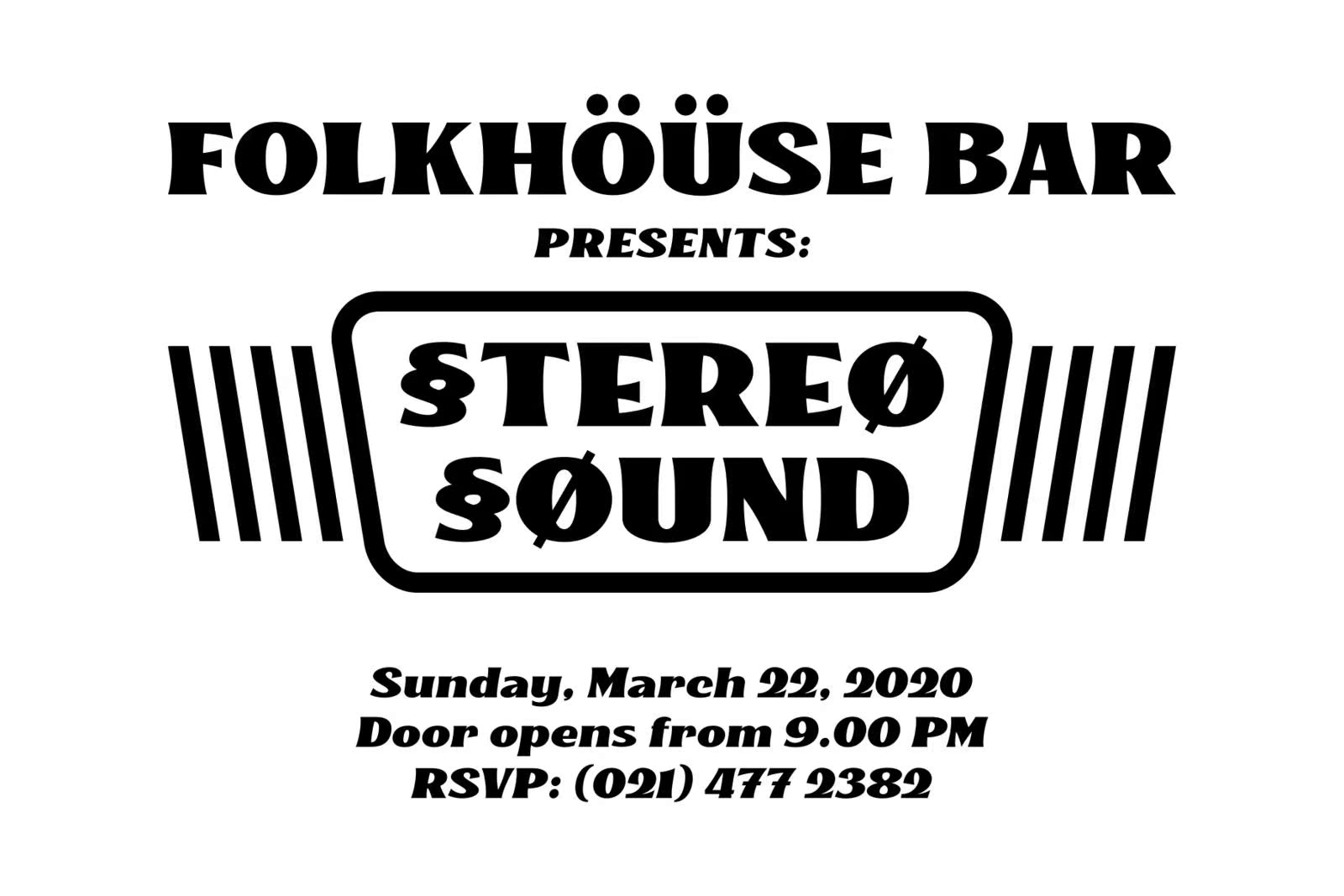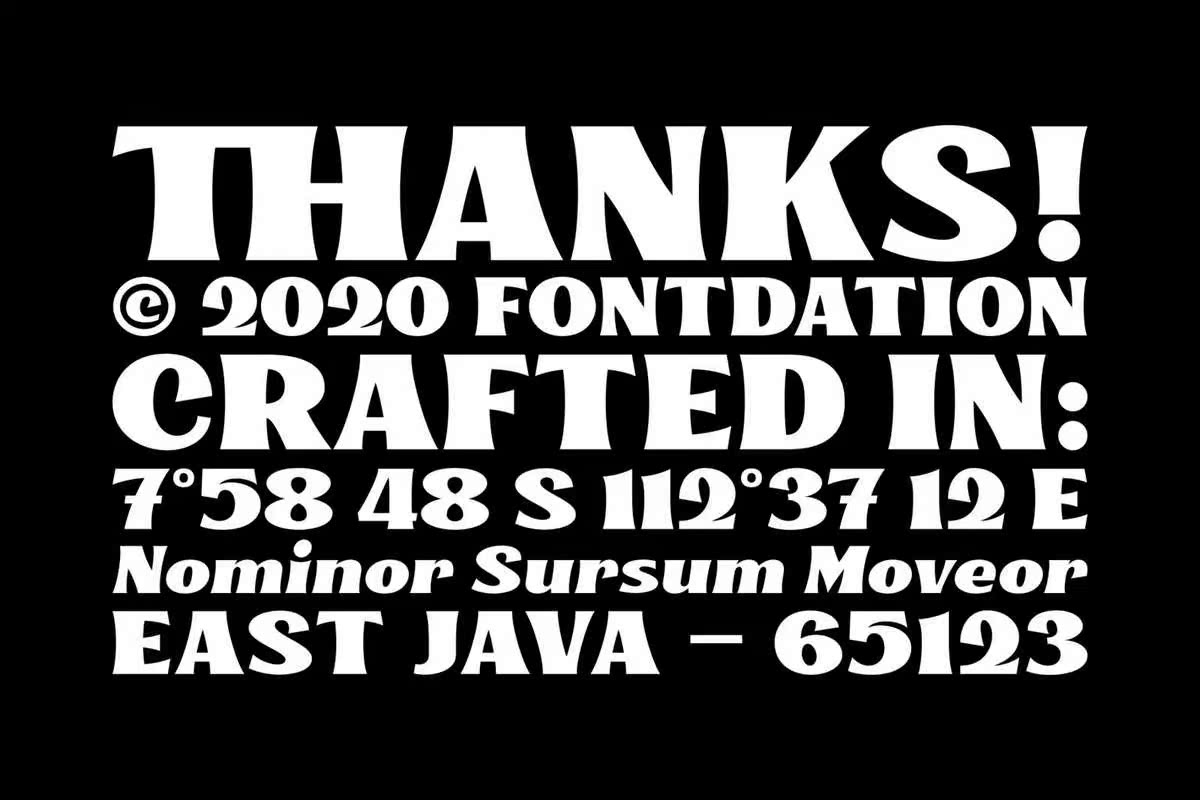
介绍GournewFontkinsaleDisplay.abold和Strong Looking显示Font,它不仅受到复古/古典风格的启发,而且还体现了现代的扭曲和荒谬。鼠标制作,高度关注细节;简洁的线条、锐利的边缘和诱人的曲线。其宽大而块状的图案形式使其成为一个巨大的空间杀手。套装的字体/标题、徽标/标识、包装/标签标志等。简介古尔纽方金萨雷显示。ABOLD和STRONG LOOKING显示字体不仅受到复古/古典图案形式的强烈影响,但也有现代的扭曲和荒谬。鼠标制作,高度关注细节;简洁的线条、锐利的边缘和诱人的曲线。其宽大而块状的形状使其成为一个巨大的太空杀手。套装字体/标题、徽标/标识、包装/标签标志等。